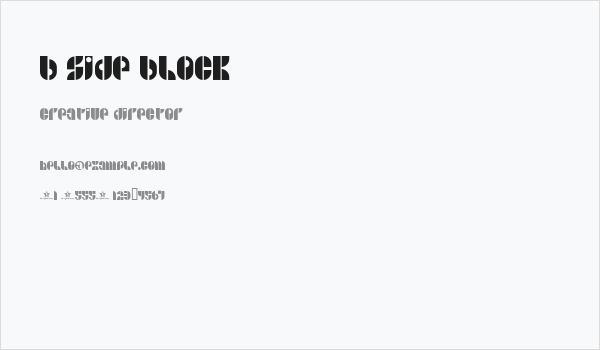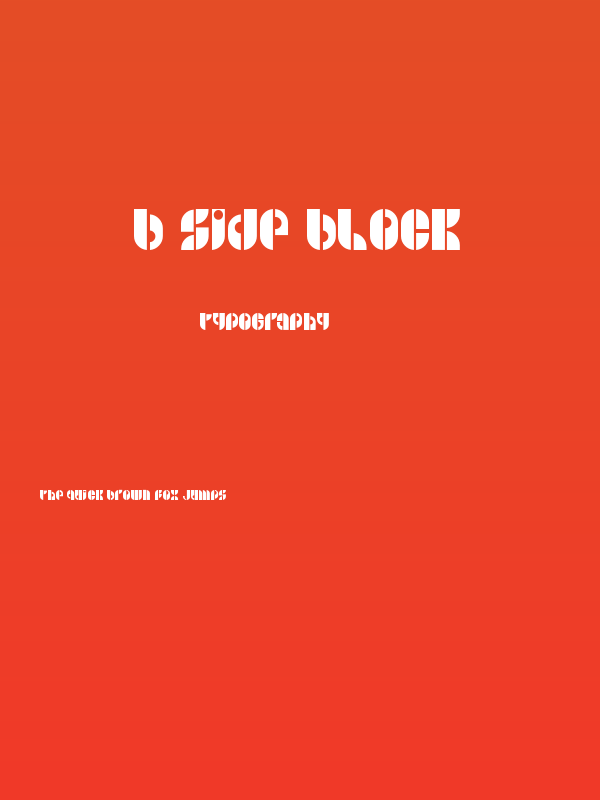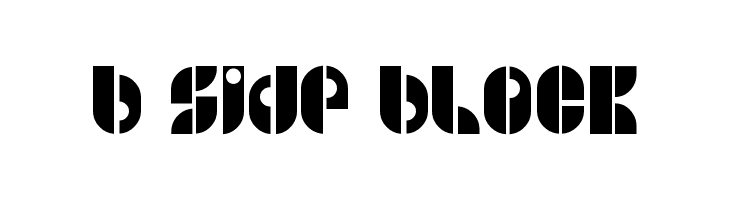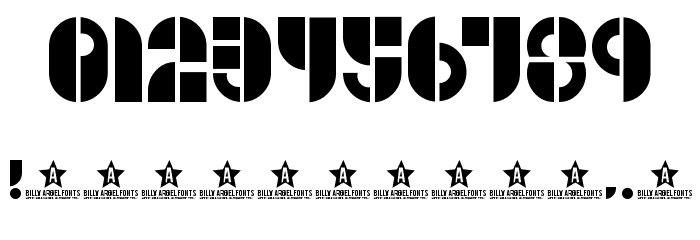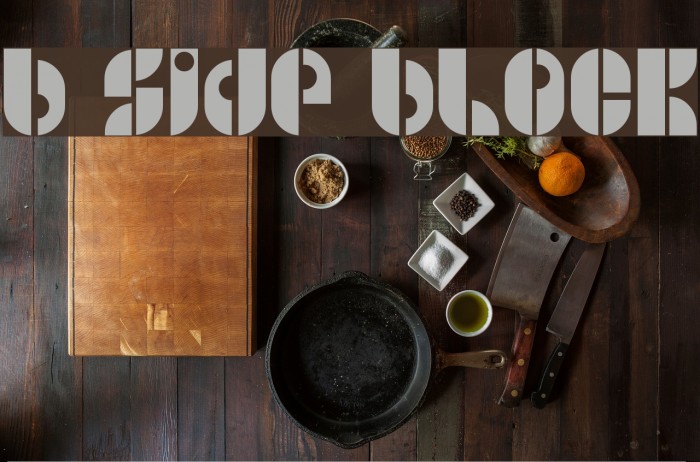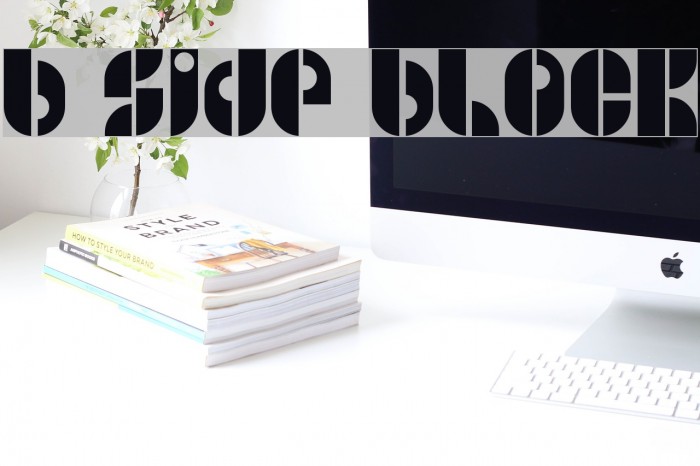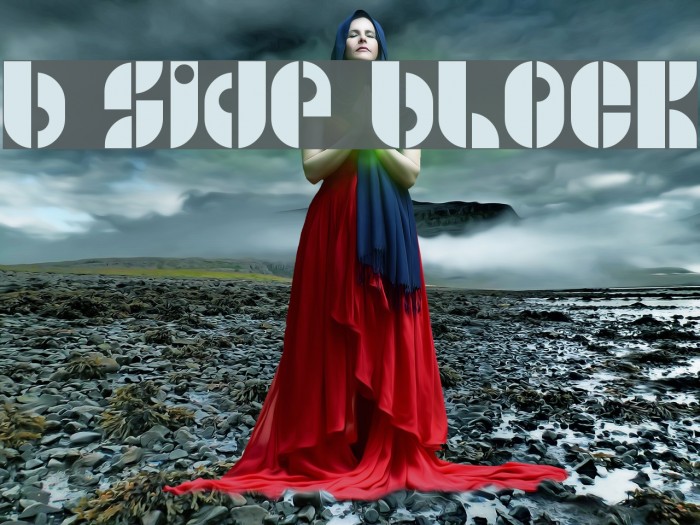
B SIDE BLOCK Font
Fonts by billyargel.blogspot.com - Billy Argel
| उपयोग का मामला | Headlines, Logos |
| सुझाए गए प्रोजेक्ट | Ideal for branding, poster design, album covers, and any project needing a bold, modern look. |